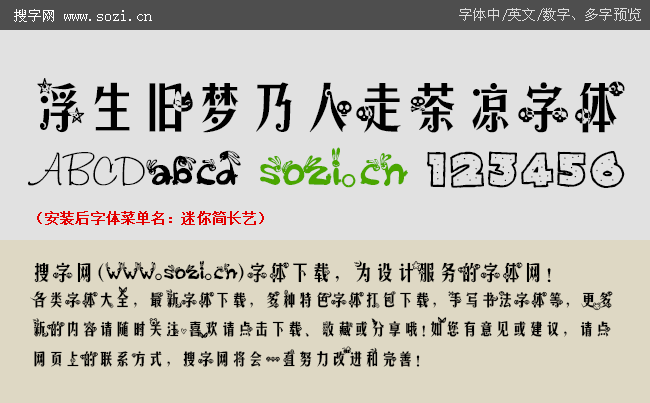
浮生舊夢乃人走茶涼字體
搜字網(wǎng)給大家提供一款浮生舊夢乃人走茶涼字體手機中文字體下載。這款手機字體是在迷你簡長藝體筆畫間插入了一些卡通圖案。筆畫既有黑體的粗壯醒目,又有宋體的秀美柔和,加上藝術性的圓球形點、起筆如蝌蚪形的頓點、螺螄轉似的小鉤,配以修長的字形,如少女般婷婷玉立,裊娜動人,美觀而不落俗套。加入了卡通圖案后又增添了趣味性,特別適合喜歡手機字體個性一些的朋友在手機上安裝使用。